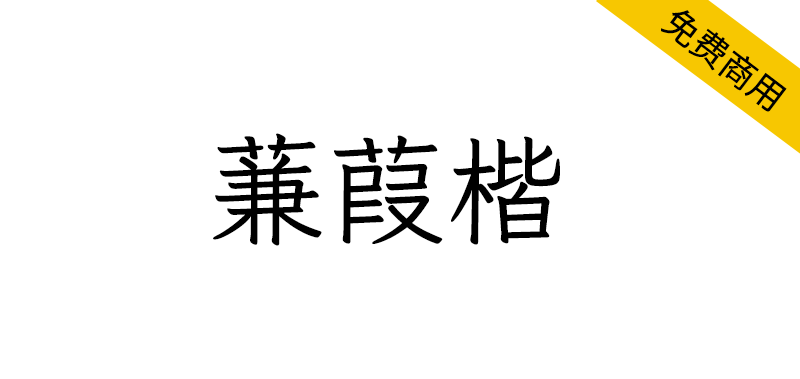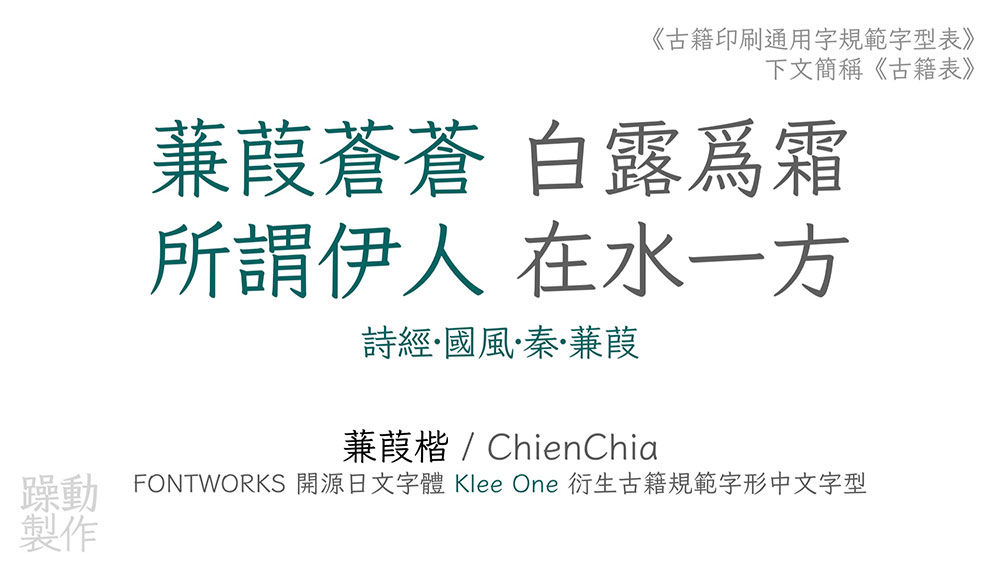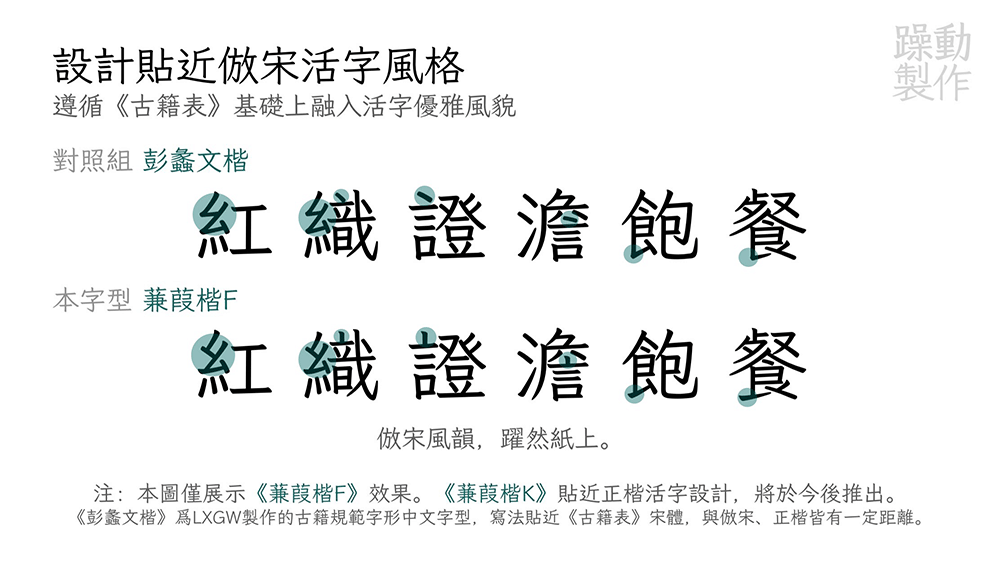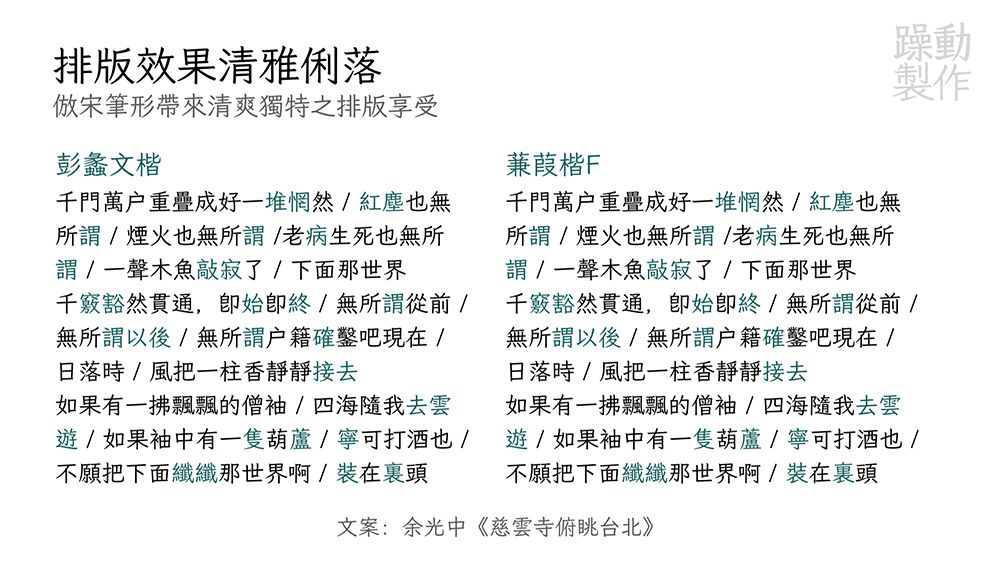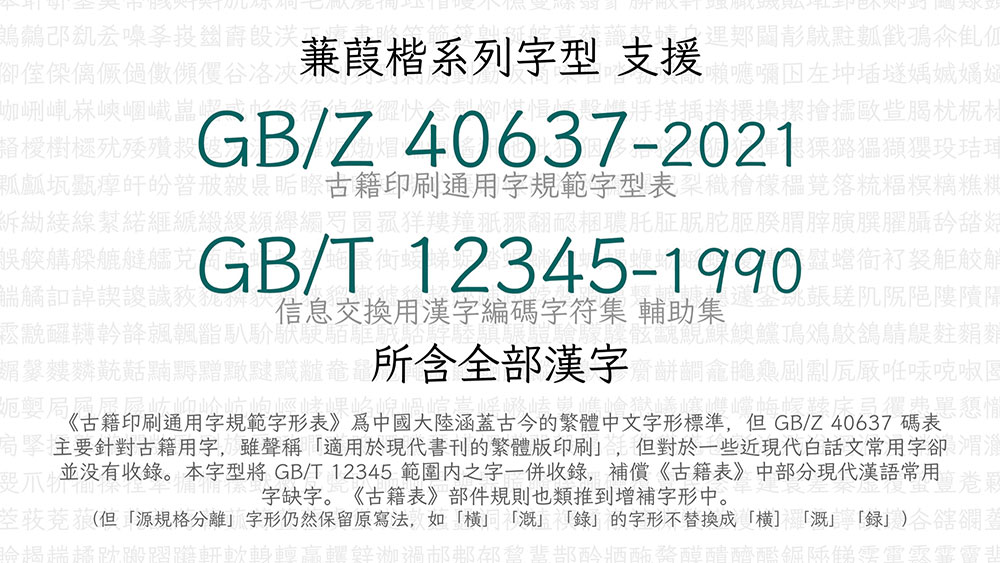
蒹葭楷是基于Fontworks(现日本蒙纳株式会社,Monotype K.K.)所发布的开源字体Klee One的衍生字体,参考《古籍印刷通用字规范字形表》(GB/Z 40637-2021)收字和调整字形。
《古籍印刷通用字规范字形表》(GB/Z 40637-2021)是新中国成立以来第一次对传世古籍印刷字的第一次整理规范,也是中国大陆第一部正式针对繁体字制定的字形规范。这部指导性技术文件声称「适用于传世古籍的印刷出版,以及现代书刊的繁体版印刷」,共收录了14,250个汉字字形,并提供每个字的首音和ISO/IEC 10646 编码。其收录GB/Z 40637-2021 范围内的全部汉字,参考GB/Z 40637-2021 所规定的字形进行调整,并计划释出分别接近仿宋和正楷活字的设计的两个版本,现接近仿宋设计的《蒹葭楷F》已开发完毕。但愿这一开源字体项目,能为《古籍印刷通用字规范字形表》颁布后的实践贡献一份绵薄之力,为古籍印刷字体提供一种新的选择。蒹葭楷字汇情况如下:
○ GB/Z 40637-2021 所收录的14,250个汉字,用于「传世古籍」所需汉字的排版与显示。
○GB/T 12345-1990 所收录的6,866个汉字,用于「现代书刊的繁体版本」所需汉字的排版与显示。
○Unicode 康熙部首区段所收录的214个部首字符,参考《康熙字典》总目中的部首字形进行取舍调整。
○全半角ASCII、拉丁补充-1区、拉丁扩展A 区、拉丁扩展B 区、国际音标扩展区、拉丁附加扩展区、注音符号。
○现代标点符号,以及古代汉语勾乙号、重文号。
○易经、太玄经、算筹、中国象棋、中国传统圆形吉祥图案等符号。